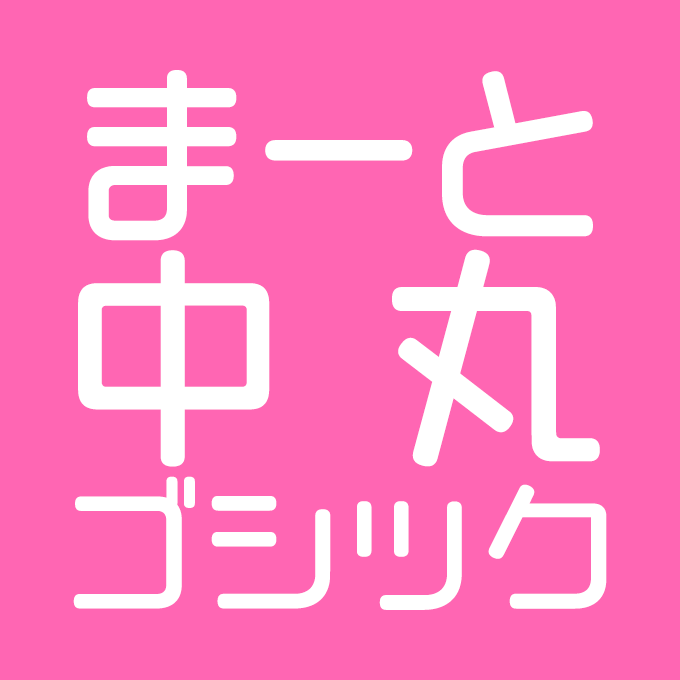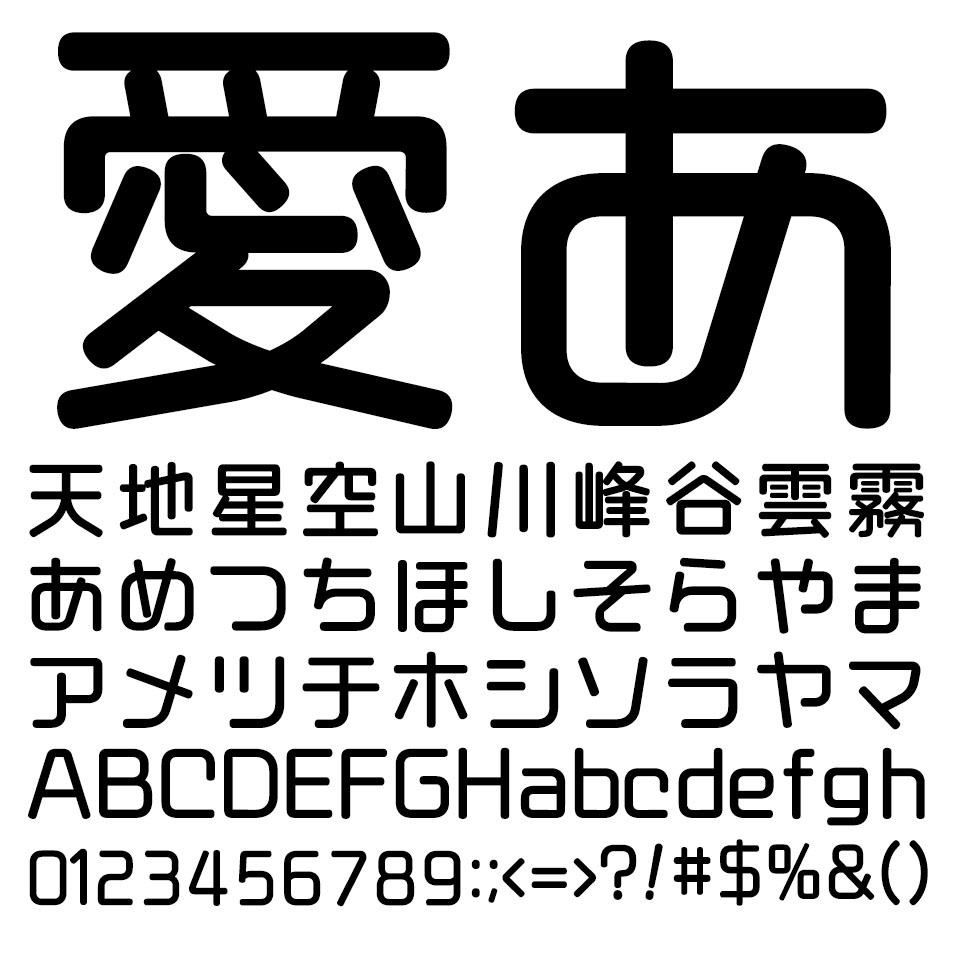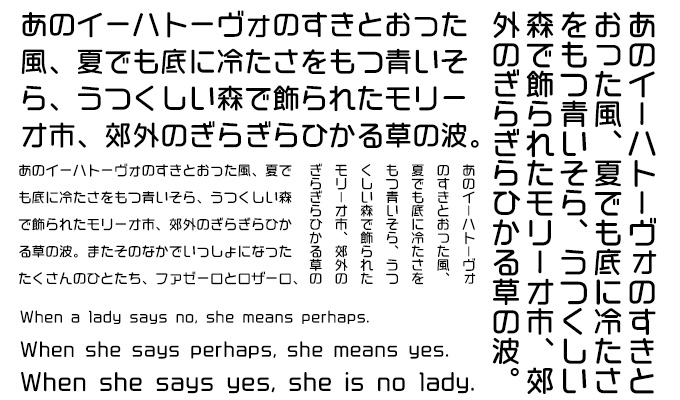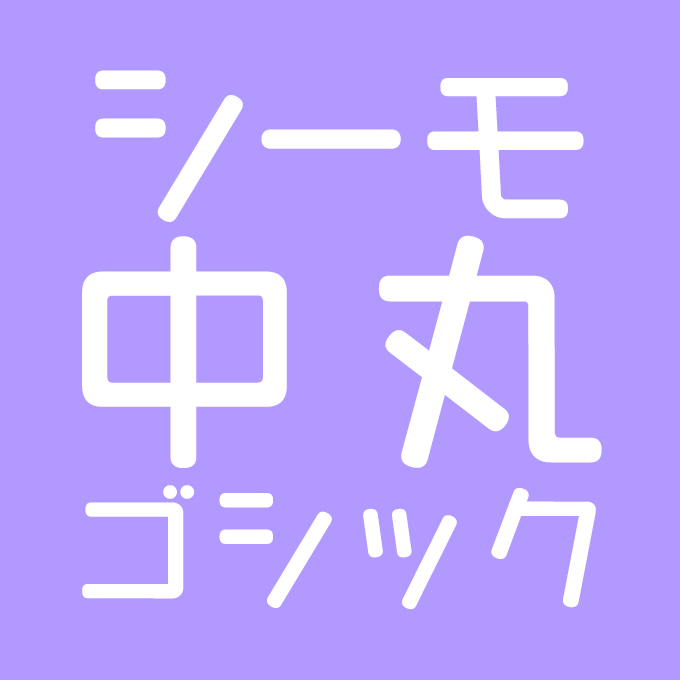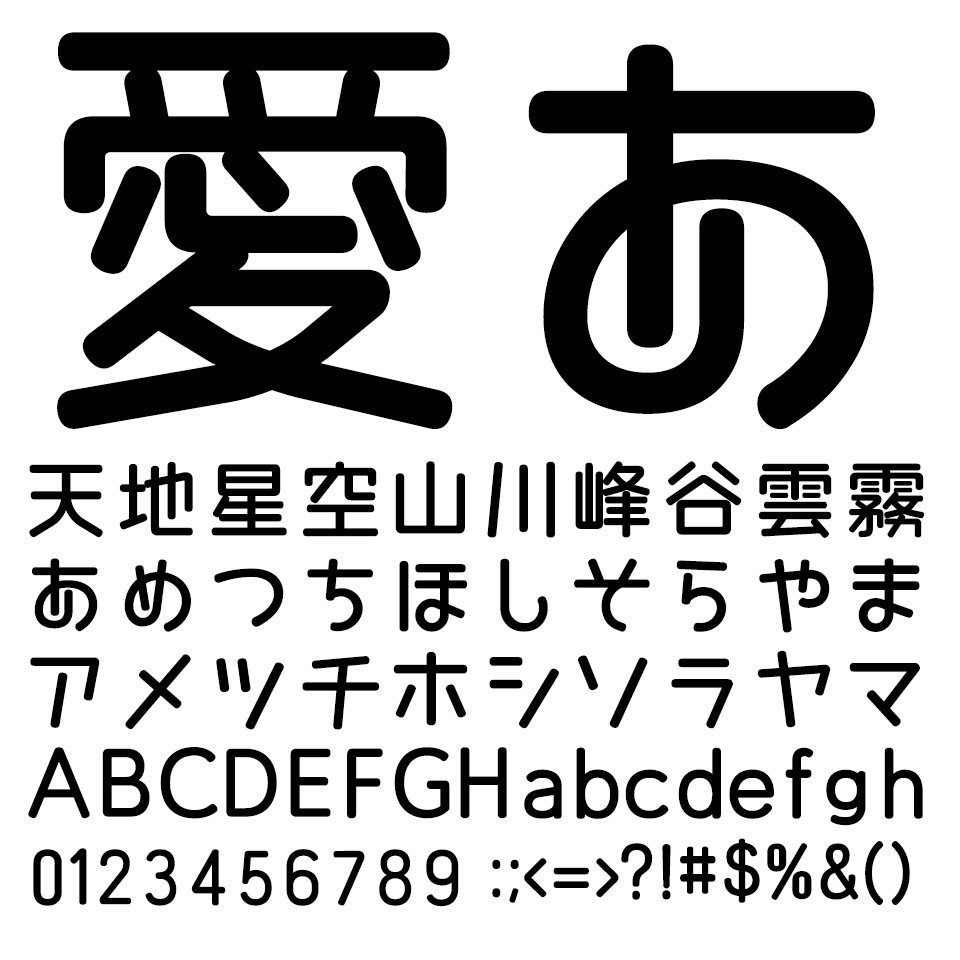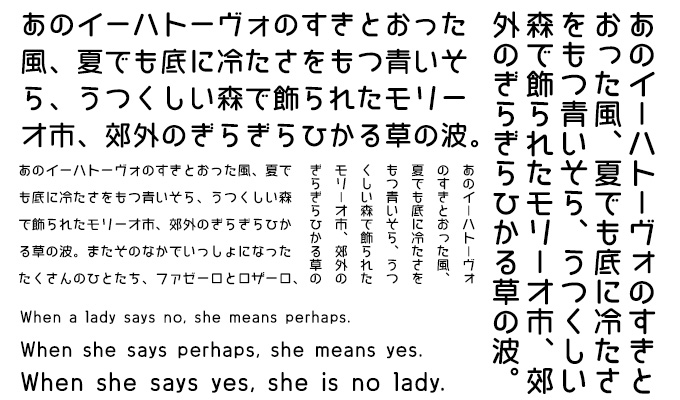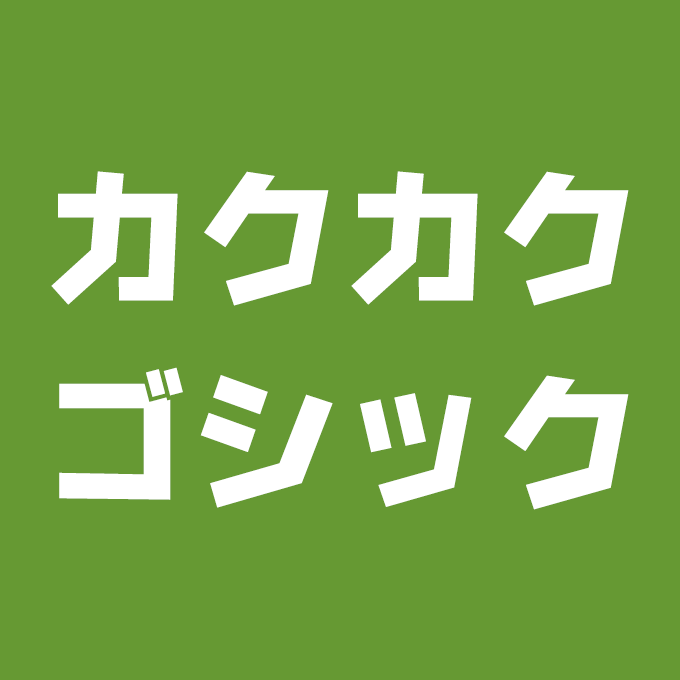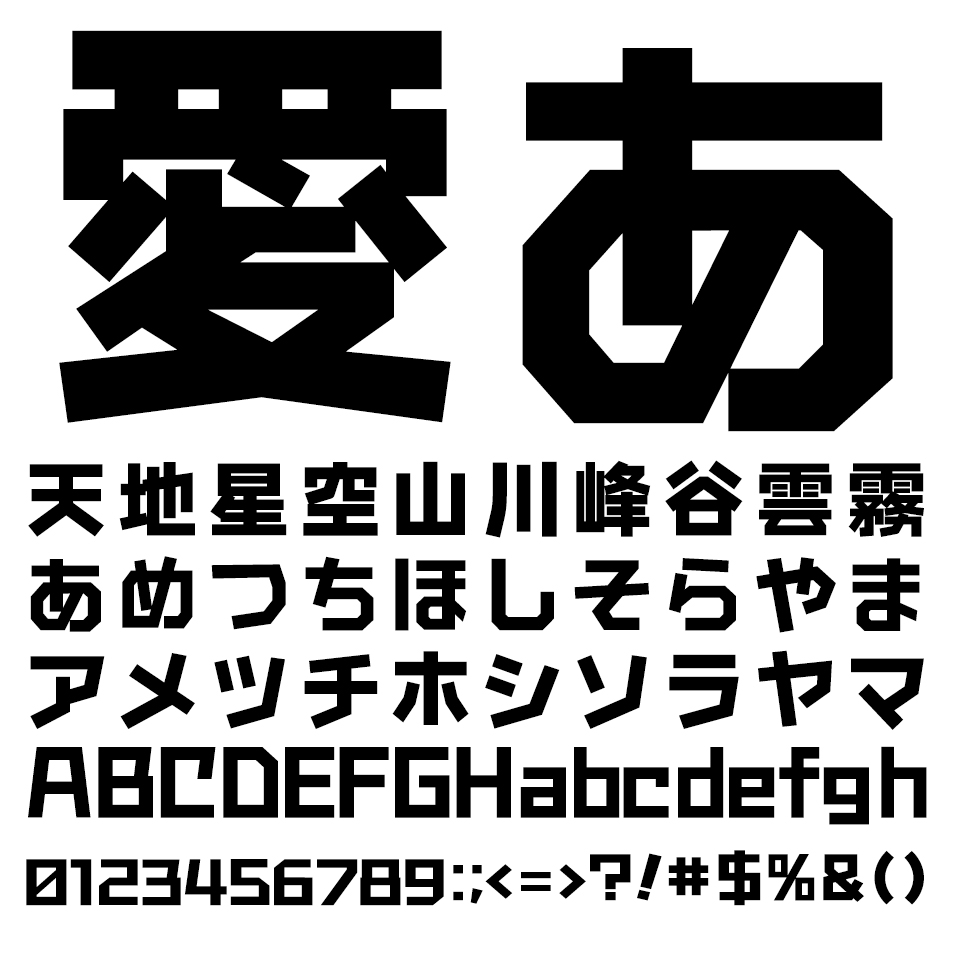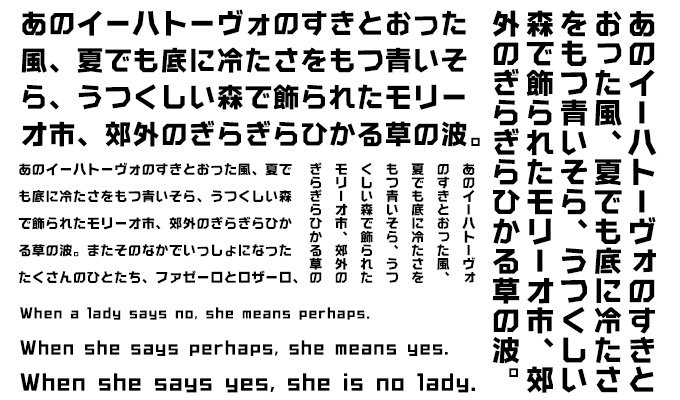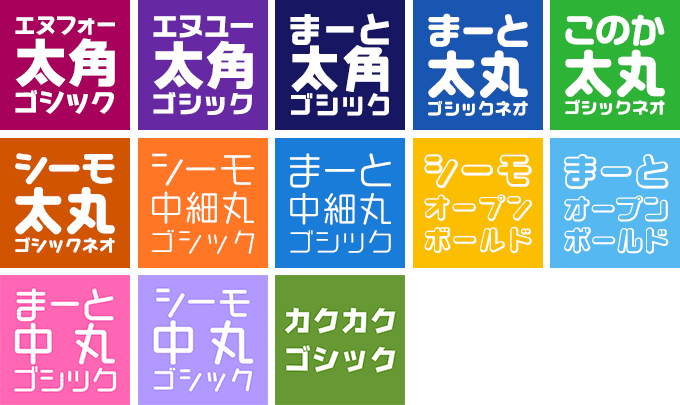
CFONT日本語10書体特別セット
キャッチコピーやタイトルを目的としたディスプレイタイプフォント CFONT
下島正人氏が手掛けるフォントライブラリー『CFONT』。キャッチコピーやタイトルを目的としたディスプレイタイプフォントを制作しており、個性的なフォルムを重視しながらも可読性も考慮されたデザインが特徴で、JIS第一水準、第二水準までの漢字を収録している使い勝手の良いデザイン書体です。
オススメの使い方
まーと太角ゴシック / まーと中細丸ゴシック / エヌフォー太角ゴシック
シーモ太丸ゴシックネオ / シーモオープンボールド / まーと太丸ゴシックネオ
シーモ中細丸ゴシック / このか太丸ゴシックネオ
CFONTのラインナップ
エヌフォー太角ゴシック
CFONT エヌフォー太角ゴシック
どっしりとした太字のフォントに遊びごころを加えて作成しました。ひらがな、カタカナは少しポップなフォルムにデザインしました。
エヌユー太角ゴシック
CFONT エヌユー太角ゴシック
どっしりとした男前のフォントをイメージして作成しました。ひらがな、カタカナは少しポップなフォルムにデザインしました。
まーと太角ゴシック
CFONT まーと太角ゴシック
角ばった字形の太角ゴシック体のフォントです。遊び心の中に多少の真面目さを表現する際に使えそうなフォントです。
まーと太丸ゴシックネオ
CFONT まーと太丸ゴシックネオ
丸ゴシックの柔らかさを残しながら、スクエアなフォルムにデザインしました。Web、ゲームなどで個性が生きる書体です。
このか太丸ゴシックネオ
CFONT このか太丸ゴシックネオ
ファンシーな優しい書体をイメージしてデザインしました。キャッチコピーやコメントをやわらかい印象にしたいときにおすすめです。
シーモ太丸ゴシックネオ
CFONT シーモ太丸ゴシックネオ
TV、DTP、Web、ゲームなどいろいろな場面で利用できる書体です。
シーモ中細丸ゴシック
CFONT シーモ中細丸ゴシック
中細丸ゴシックで柔らかさより、幾何学的なフォルムをイメージしてデザインしました。タイトルなどで、やや大きく使用すると面白い書体です。
まーと中細丸ゴシック
CFONT まーと中細丸ゴシック
丸ゴシックなのに、直線を意識したフォルムでオリジナリティを追求しました。スペースいっぱいにデザインされ、可読性よりユニーク性を強調しました。
シーモオープンボールド
CFONT シーモオープンボールド
ポップな表情が面白い効果を生むフォントです。DTP、WEB、ゲームと多岐に使用できるフォントです。
まーとオープンボールド
CFONT まーとオープンボールド
ポップな表情が面白い効果を生むフォントです。DTP、WEB、ゲームと多岐に使用できるフォントです。
こんなところでCFONT
この素晴らしい世界に祝福を!(コミック版)
『この素晴らしい世界に祝福を!』角川スニーカー文庫
「この素晴らしい世界に祝福を」のコミック版のロゴでは、漢字は「まーと太角ゴシック」、ひらがなは「やさしいキモチつながるココロ」が使用されています。
まーと太角ゴシック
角ばった字形の太角ゴシック体のフォントです。遊び心の中に多少の真面目さを表現する際に使えそうなフォントです。「まーと太角ゴシック等幅」は1バイトのJISローマ字・半角カタカナの幅が50%の統一設定になっています。